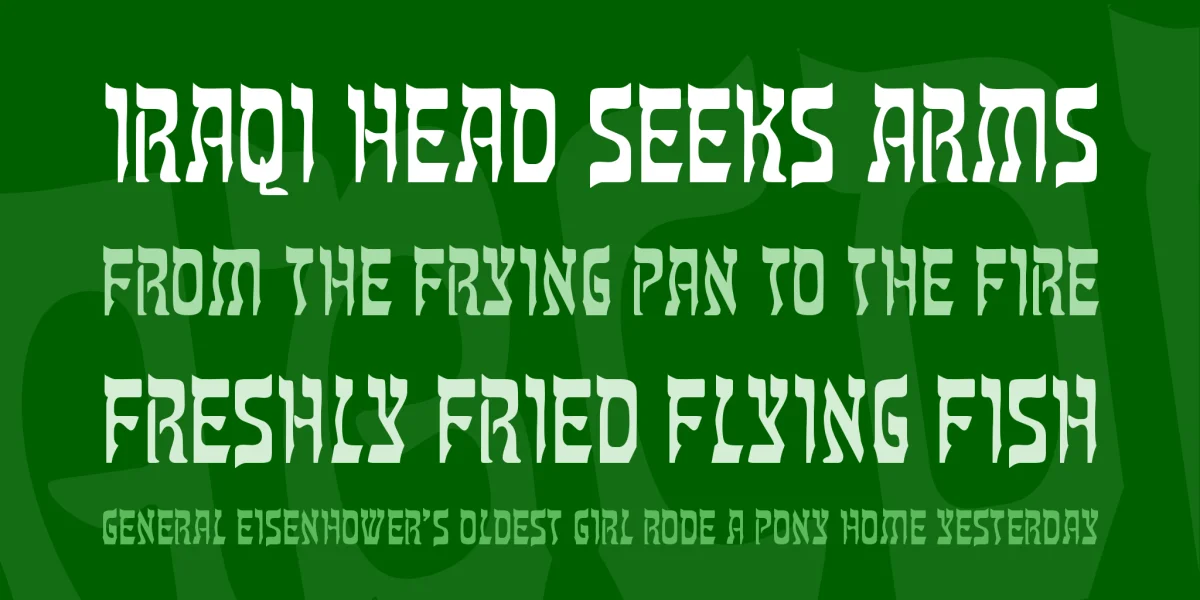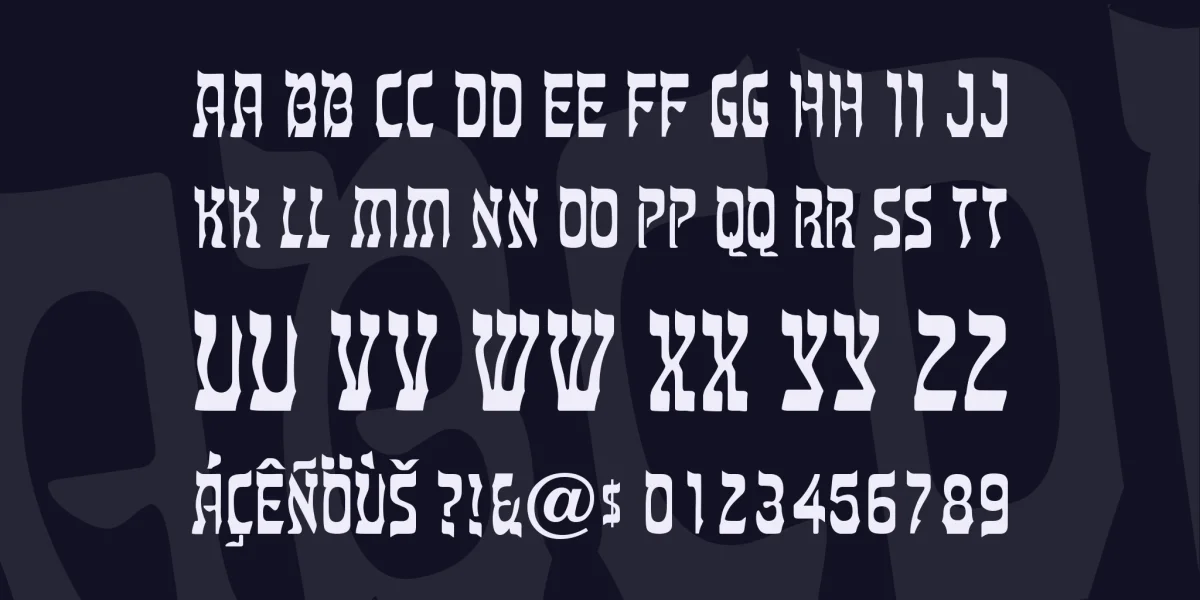
Tanach ist eine Antiqua, die hebraeische Buchstaben nachahmt. Geeignet fuer Plakate und Betitelung mit Bezug zu Israel oder dem Judentum. (Tanach ist der Name fuer die hebraeische Bibel)